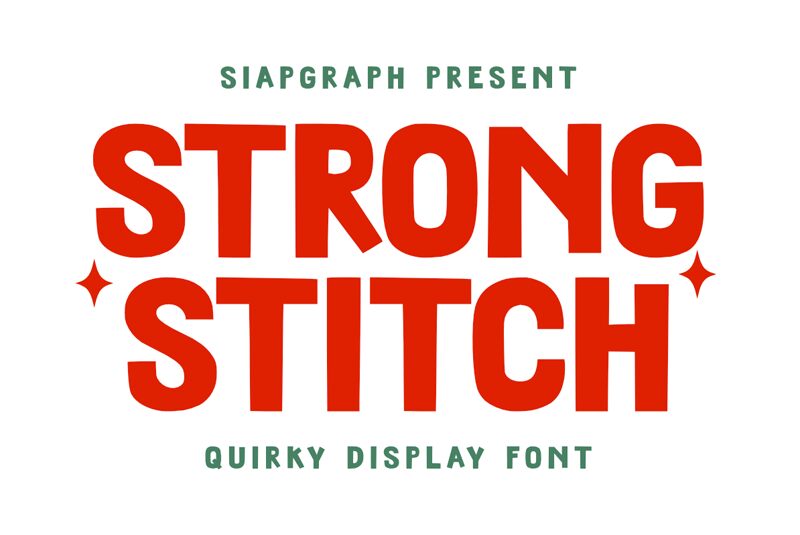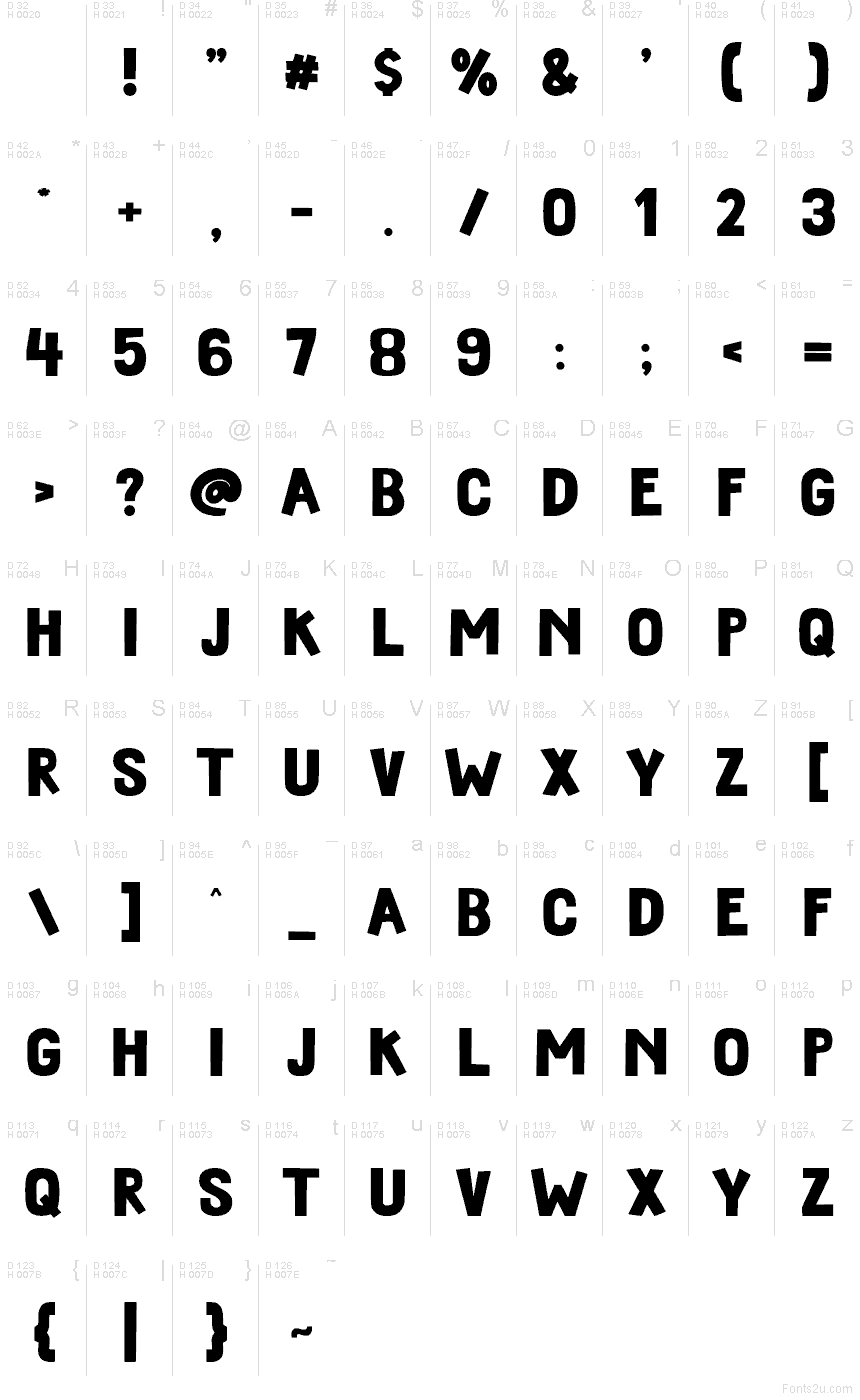
Strong Stitch Regular
Strong Stitch od SiapGraph je bezplatné komiksové display písmo, ktoré definujú široké, hranaté tvary a kompaktná silueta ideálna na plagáty. Písmená pôsobia ako vyrezané z masívnych blokov, s kombináciou zaoblených vonkajších kriviek a niekoľkých ostrých diagonálnych rezov, vďaka ktorým nepôsobí len ako obyčajné geometrické bezpätkové písmo.
Táto kompaktná hmota dodáva krátkym titulkom na herných miniatúrach, športových letákoch, plagátoch na akcie pre mladých, obaloch a výraznej grafike na sociálnych sieťach skutočnú autoritu. Skvele funguje aj v návrhoch log a nadpisoch, kde robustné tvary obstoja aj proti rušnému pozadiu a výrazným farbám.